书法是很多人平时必学的一门课程,可是并不是只要付出了认真和时间以后就能够有好的作品,所以看到书法字体大全里其他人写出来的字体以后,总会有非常钦羡和想要拥有的。虽然说自己技不如人,但是可以通过借鉴来提升水平,而平时真正要求自己动手书写的情况不多见,有时是用于工作,那可以通过书法字体大全去寻找现成的素材。
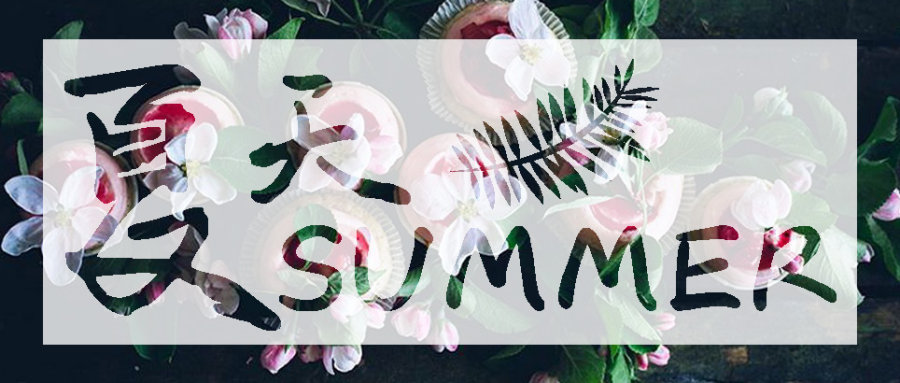
不乏有些人平时会私下里练书法,但是却并没有太大的进步,这是因为需要有所参考,其实除了字帖以外,还可以利用书法毛笔字体转换器字体大全。大家可以从中选择一种或者多种来仿照书写,久而久之就会有成效。另外有些人是在网络上用这种字体,看起来比较优雅,也适用于多个场合,而自己是没有能力创作的,还不如直接下载他人上传的佳作。
既然书法字体大全存在的价值还是比较高的,那么究竟应该如何去选择和使用呢?毕竟大家随后搜索可能就会出现很多的成品结果,重要的还是看是否能够符合自己的欣赏水准,毕竟这种字体其实也有不同的风格,有些比较潦草有些比较规范等。